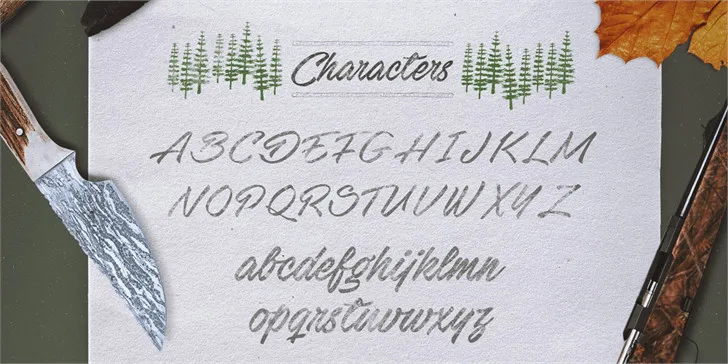
Stackyard font – Download Grátis
A Stackyard PERSONAL USE é uma fonte criada por Måns Grebäck no ano de 2015, dedicada ao gosto pelo estilo árabe e chinesa. Suas linhas fluidas e curvas delicadas fazem dela um recurso ideal para quem deseja adicionar um toque especial em designs de arte ou gráficos digitais. Inspirada na calligrafia oriental, essa fonte é perfeita para quem busca uma maneira única de expressar suas ideias, seja através de design editorial, publicações online ou até mesmo arte digital. Ideal para os amantes da cultura asiática e dos estilos artísticos únicos, a Stackyard PERSONAL USE oferece um conjunto variado de caracteres que não apenas torna seu trabalho único, mas também adiciona uma nota de elegância ao seu design. Embora esteja disponível apenas para uso pessoal por razões de direitos autorais, o Stackyard é um recurso imensuravelmente valioso para aqueles que desejam incorporar elementos de artes asiáticas em seus trabalhos digitais. Suas linhas leves e fluidas permitem uma mistura perfeita com outros tipos de fonte ou mesmo outras formas de arte, permitindo que você use seu talento criativo para criar designs únicos e imprimíveis. Sem dúvida, é um recurso indispensável para qualquer designer ou artista interessado em incorporar elementos do design asiático em seus trabalhos.